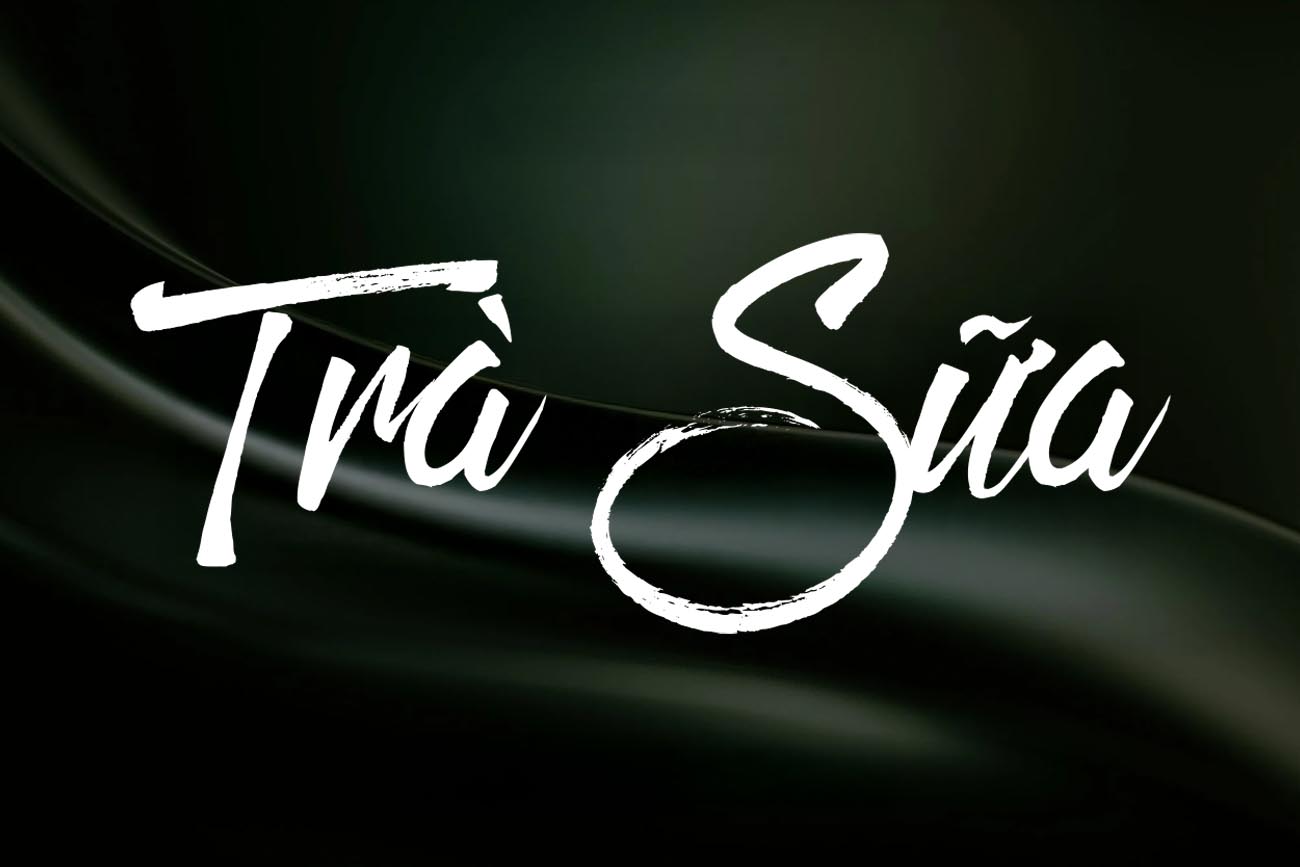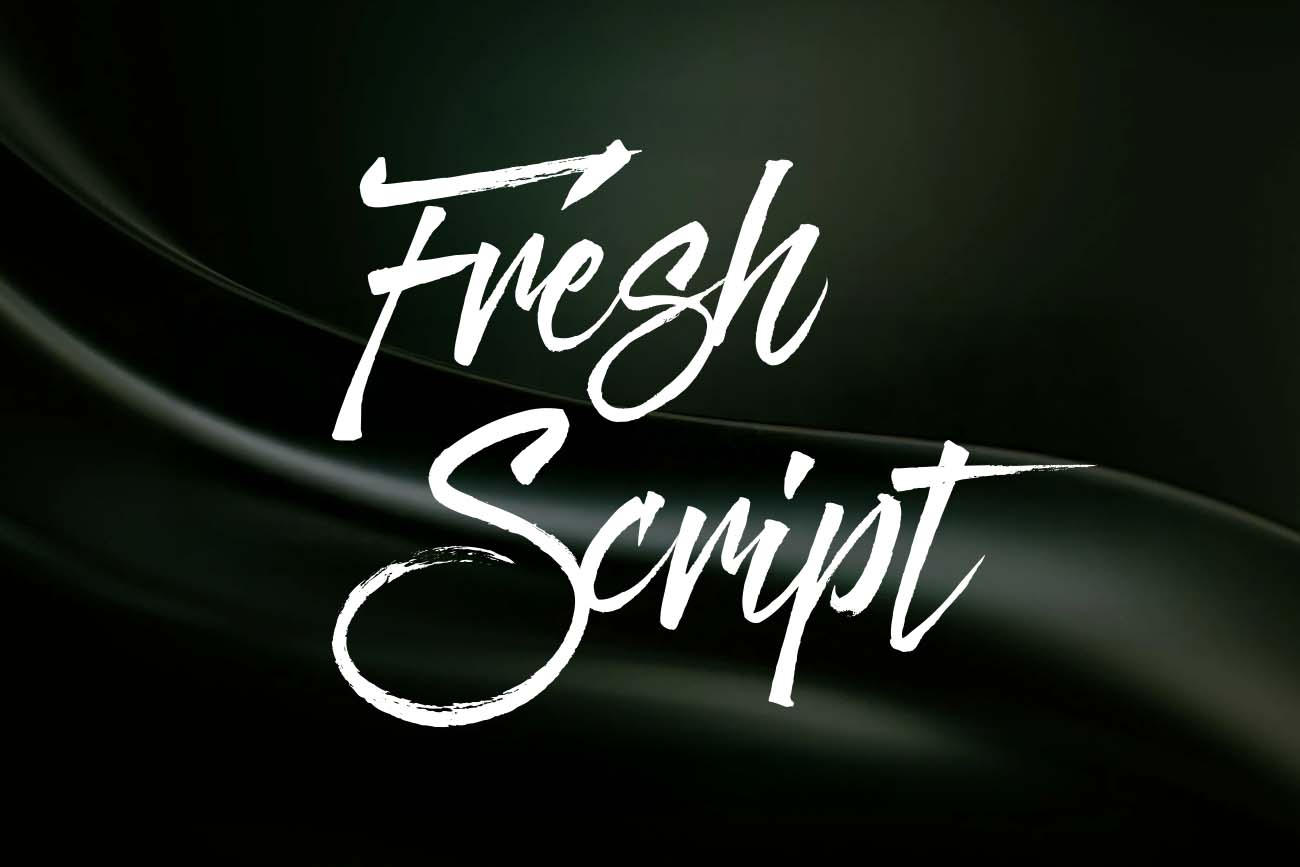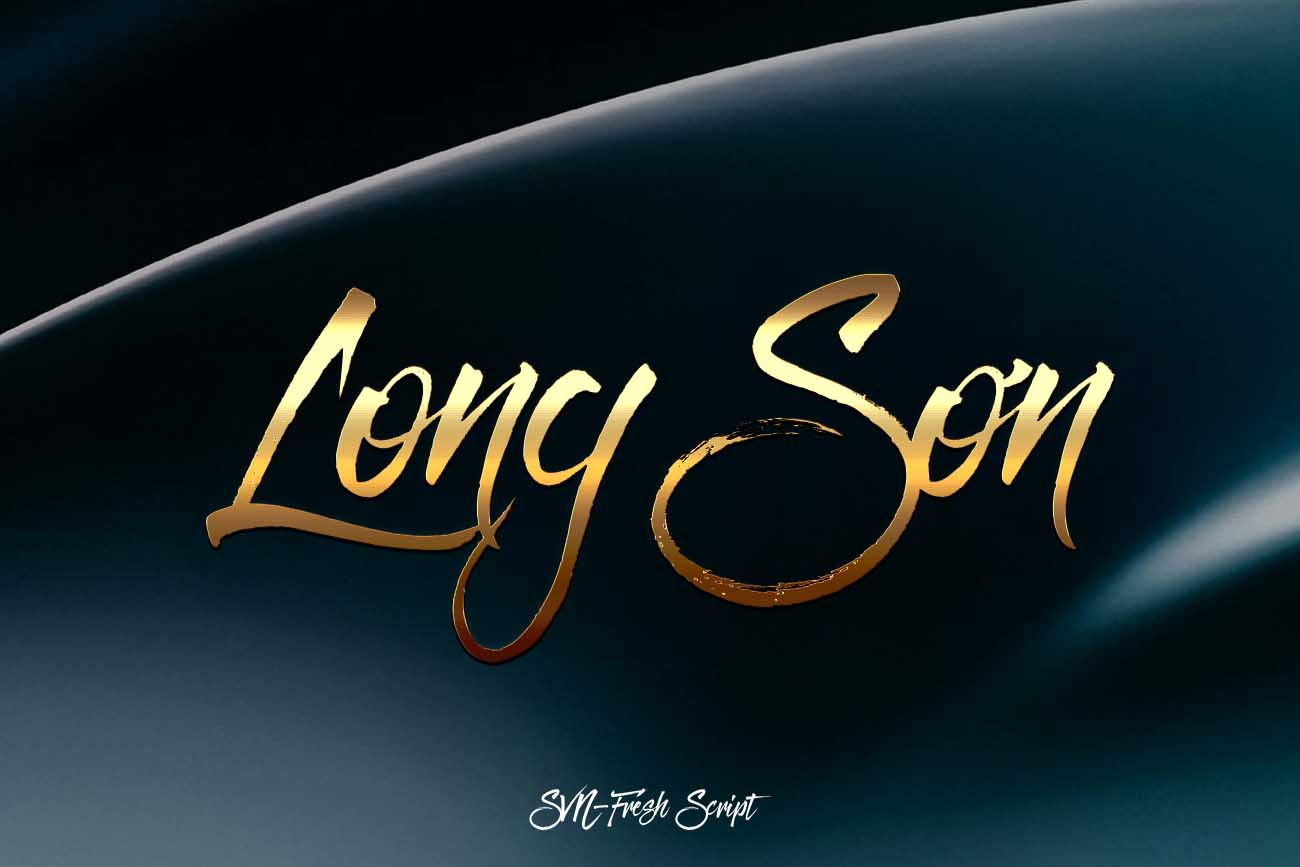
[Tải Về] Font Chữ Brush SVN-Fresh Script Việt Hóa – Mạnh Mẽ, Cá Tính & Đậm Chất Nghệ Thuật
SVN-Fresh Script (hay còn viết là svn fresh script) là một font chữ brush Việt hóa nổi bật với phong cách tự do, táo bạo và đầy năng lượng. Nét chữ vung tay mạnh mẽ, như được viết bằng cọ mực thật, tạo nên hiệu ứng thị giác ấn tượng, rất phù hợp cho những thiết kế cần nhấn mạnh chất cá nhân và tinh thần sáng tạo.
Nguồn gốc & Việt hóa:
Font gốc được thiết kế bởi Set Sail Studios – một studio nổi tiếng với các bộ font mang phong cách viết tay cá tính, phóng khoáng. Với Fresh Script, họ đã tạo nên một bộ font đậm chất brush, lấy cảm hứng từ các nét vẽ tay tự do bằng bút lông hoặc marker. Sau đó, SVN Fonts (STYLEno.1 Fonts) đã Việt hóa toàn bộ font này, hỗ trợ đầy đủ tiếng Việt, tối ưu hiển thị và giữ nguyên thần thái mạnh mẽ của bản gốc.
Đặc điểm nổi bật:
• Thiết kế theo dạng font chữ viết tay brush, mô phỏng đường cọ vẽ tay sống động, đậm chất nghệ thuật.
• Ký tự có độ đậm – nhạt rõ ràng, chuyển động linh hoạt, tạo nên vẻ mạnh mẽ, không gò bó hay cứng nhắc.
• Font Việt hóa đẹp, hỗ trợ đầy đủ dấu tiếng Việt – dùng tốt cho mọi mục đích thiết kế tiếng Việt hiện đại.
Ứng dụng linh hoạt:
• Logo thương hiệu cá tính, thời trang đường phố (font chữ streetwear)
• Poster, tiêu đề, trích dẫn truyền cảm hứng
• Bao bì mỹ phẩm, handmade, tạp chí nghệ thuật
• Dự án cần chất liệu font chữ mạnh mẽ & cá tính
SVN-Fresh Script không chỉ là một font Việt hóa đẹp, mà còn là một lựa chọn lý tưởng cho những ai đang tìm kiếm phông chữ viết tay Việt hóa mang cá tính riêng, chất nghệ và tinh thần tự do. Với sự kết hợp giữa nét viết tay truyền cảm và độ linh hoạt trong ứng dụng, font sẽ là điểm nhấn sáng tạo trong bất kỳ thiết kế nào.